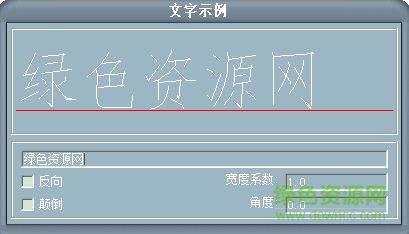
hdhz.shx字體是cad中一款非?;鸨淖煮w,是朋友們?cè)谶M(jìn)行特殊英文文章書(shū)寫(xiě)時(shí)所常用的字體之一,其字體形式也非常的具有特色,而且在本站下載之后即可免費(fèi)安裝使用,無(wú)限付費(fèi),有需要的朋友就請(qǐng)來(lái)綠色資源網(wǎng)下載體驗(yàn)吧!